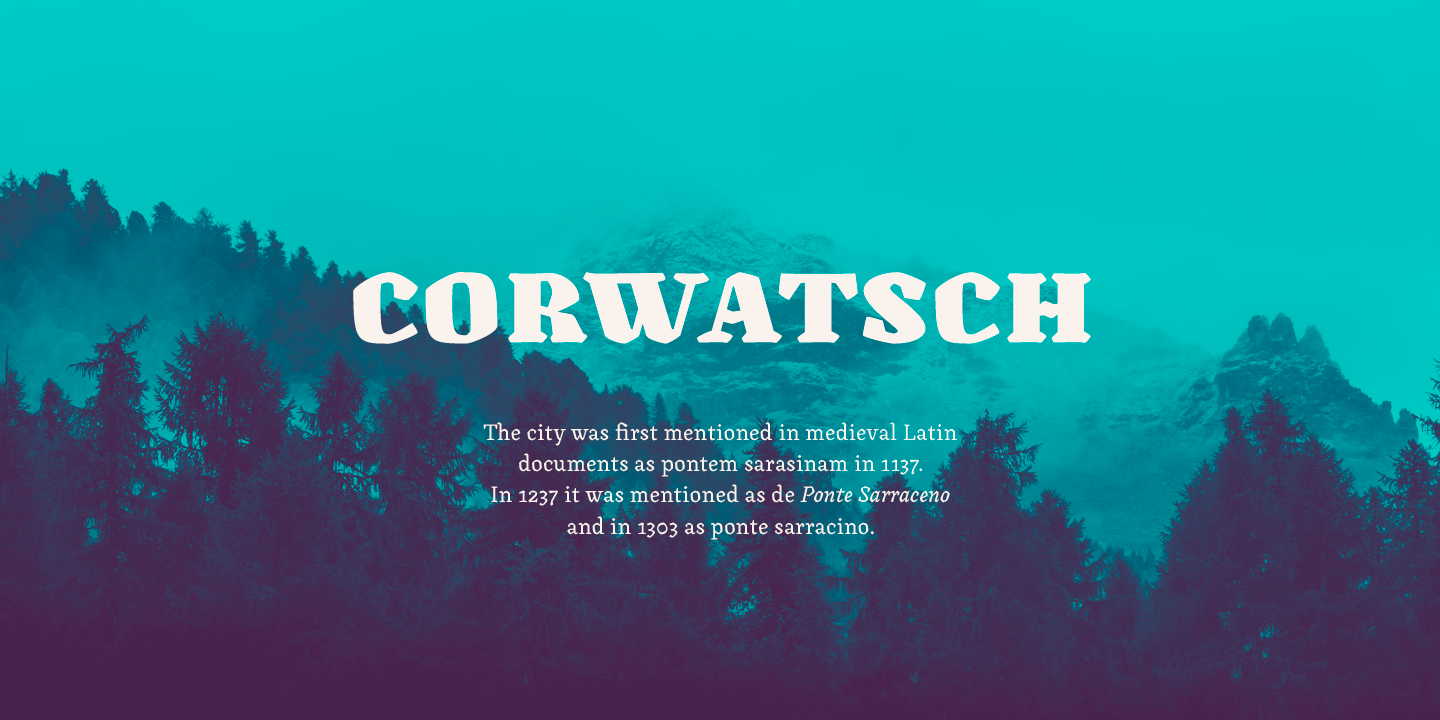
Logo nan bagus memerlukan tiga hal: gambar, nama brand, dan tagline. Dalam proses kreasi logo, kalian pasti wajib menentukan font untuk logo Anda.
Font logo tersedia dalam beragam bentuk dan ukuran, dan font nan kalian pilih untuk membuat logo dapat mempengaruhi persepsi pengguna kepada brand Anda.
Untuk membantu kalian mendapatkan logo nan menarik, kami telah membikin daftar 43 font logo terbaik untuk membangun gambaran perusahaan Anda.
43 font untuk logo minimalis dan elegan
Tidak mungkin untuk memilih hanya satu tipe huruf nan terbaik untuk logo brand Anda.
Ada begitu banyak font logo, nyaris sebanyak tipe bisnis nan berbeda, dan masing-masing font dan bisnis mempunyai karakter unik nan berbeda.
Font terbaik untuk logo ialah font nan bisa membawa identitas suatu brand atau perusahaan.
Itulah kenapa tak mungkin untuk membandingkan font ahli dan font minimalis dengan tipe huruf modern dengan font klasik dan font komersial dengan tipe huruf serif.
1. Baltica
Pertama, kita punya Baltica. Sebuah kreasi font serif nan mempunyai huruf sederhana nan bisa dibaca, dua karakter krusial dari sebuah logo.
Sebelum melanjutkan, krusial untuk diketahui bahwa font serif ialah font nan huruf-hurufnya mempunyai garis-garis mini nan keluar dari tepinya, seperti pada contoh di atas. Sedangkan font sans serif tak (kita bakal memandang banyak dari mereka nanti).
Serif tipis dan lurus membedakan Baltica dari personil family font serif lainnya. Alhasil, kreasi Baltica kelihatan tradisional dengan sedikit sentuhan modern.
Terlepas dari kreasi biasa, Baltica juga datang dengan berat ekstra kental. Wujudnya nan berani ialah apa nan diketahui sebagai font slab serif. Slab serif amat ideal bagi mereka nan mau membikin kesan nan lebih kuat.
2. Steak
Steak termasuk dalam family script typeface dan amat cocok jika kalian mau kreasi tipografi logo kalian kelihatan elegan namun menyenangkan.
Restoran kelas atas atau jasa aktivitas tertentu bisa mempertimbangkan untuk menggunakan tipe huruf seperti Steak untuk merek mereka.
Font kursif ini mempunyai tampilan kelas atas. Sementara itu, ekor panjang nan berputar-putar menambah kepribadian pada tipe huruf.
Meskipun font kelihatan dekoratif, setiap huruf tetap terbaca. Namun, jika kalian memutuskan untuk menggunakannya untuk logo, jangan lupa untuk menguji tampilan kreasi pada layar nan lebih kecil.
Font ini datang dalam tiga jenis: barbecue, braised dan smoked.
Desain asap menampilkan pengaruh terkikis, menjadikannya pilihan nan bagus jika kalian mau menambahkan sentuhan vintage pudar pada kreasi logo Anda.
3. Futura
Siapa nan tak mengenal Futura? Keluarga font ini telah digunakan berulang kali oleh merek logo terkenal seperti Best Buy, Calvin Klein, Domino’s Pizza dan adalah bahan pokok dalam daftar 10 besar terkemuka.
Jelas mengapa. Futura datang dalam beragam gaya, dari ringan, tebal, dan berat hingga miring dan kental. Keragaman memungkinkan bisnis apa pun untuk memanfaatkan tipe huruf serbaguna ini.
Karena bentuk hurufnya nan geometris, kreasi Futura kelihatan sederhana, bersih, dan modern. Karena setiap huruf mempunyai ketebalan nan sama, font gampang dibaca di layar mana pun.
Namun, ada sesuatu nan mungkin belum kalian ketahui seputar Futura. Dan itu ialah bagian dari family font nan disebut Akzidenz-Grotesk. Ini ialah salah satu sans serif dan style font ini digunakan secara tertentu untuk tujuan kreasi komersial.
Futura dan Akzidenz-Grotesk ialah contoh gimana desainer skematis permulaan beranjak untuk membikin tipe huruf tertentu untuk digunakan dalam kreasi logo.
Tidak heran jika font ini amat terkenal di merek logo modern.
Karena itu, kalian perlu berkarya dengan kreasi logo kalian jika mau menggunakannya.
Jika tidak, kalian bisa kelihatan seperti salinan murah dari sejumlah logo nan telah ada selama separuh abad.
4. Frutiger
Frutiger ialah font sans-serif lain nan amat bagus. Awalnya dirancang untuk tanda-tanda bandara, itu dibuat untuk keterbacaan maksimum di layar apa pun.
Kejelasan kreasi inilah nan menjadikannya salah satu font terbaik untuk logo.
Seperti kebanyakan font modern, Frutiger amat cocok untuk layar besar dan kecil. Seperti Futura, bentuknya nan bersih dan sederhana membikin font ini elastis untuk digunakan dalam kreasi logo komersial.
Keluarga font juga datang dalam beragam style mulai dari nan paling ringan hingga nan paling berani.
Font Frutiger nan kalian lihat hari ini sebenarnya ialah pembaruan untuk tipe huruf klasik Adrian Frutiger, telah dikerjakan ulang oleh Akira Kobayashi, desainer Jepang di kembali Monotype, dan kalian bisa menemukannya dari banyak merek terkenal, termasuk Ericsson dan RadioShack.
5. Garamond
Garamond ialah font terkenal nan telah dibuat ulang dalam beragam gaya. Beberapa tipe terkenal nan digunakan ketika ini adalah Adobe Garamond dan EB Garamond.
Seperti seluruh font Adobe, Adobe Garamond disebut sebagai font OpenType. Fitur OpenType mencakup fungsionalitas lintas platform (walaupun itu tak menjadi masalah untuk beberapa waktu). Saat ini, font OpenType lebih diketahui sebagai font cuma-cuma untuk penggunaan komersial, menjadikan Garamond salah satu font paling terkenal untuk desainer.
Serif dalam tanda kurung atau kurva ialah karakter utama dari tipe huruf. Ini juga mempunyai sedikit ragam stroke nan memberikan bentuk nan dinamis.
Garamond ialah pilihan nan amat bagus bagi mereka nan mau kreasi logo mereka kelihatan kekal dan halus, seperti perusahaan nan merambah ke mode atau perhiasan.
Jika kalian mau membikin tampilan nan lebih kuat dengan Garamond, coba gunakan nama bisnis Anda, seperti logo lama American Eagle Outfitters:
6. Baskerville
Untuk pilihan Garamond, pertimbangkan Baskerville. Wujudnya mempunyai kepribadian elegan nan serupa, tetapi font ini mempunyai beberapa fitur nan membuatnya khas.
Misalnya, beberapa huruf font mempunyai tepi nan sedikit lebih tajam. Dan, tak seperti Garamond, serif adalah transisi daripada kuno.
Karena penampilannya nan elegan, Baskerville bisa menjadi tipe huruf logo nan amat bagus untuk merek-merek mewah, seperti Kate Spade.
Baca Juga: Desain Kaos Custom Terbaik Untuk Seragam Acara
7. Helvetica
Helvetica ialah salah satu font sans serif nan paling diketahui di pasaran. Ini telah digunakan oleh banyak merek terkenal, termasuk logo perusahaan seperti Panasonic dan Target, dan terkenal dalam kreasi web.
Anda kemungkinan besar bakal menemukan Helvetica di 10 font teratas atau daftar 10 kreasi teratas.
Dan itu lantaran Helvetica praktis mendominasi pasar tipe huruf komersial di seluruh bumi dan malahan menyebar ke kreasi web dan pengolah kata.
Dari segi tampilan, mirip dengan open sans, bentuk hurufnya sederhana dan goresannya sama tebalnya, menjadikannya font nan amat gampang dibaca. Popularitasnya telah menghasilkan banyak riff dalam style aslinya, seperti layar ekstra hitam.
Helvetica datang dalam beberapa gaya, termasuk bentuk bulat nan digunakan dalam kreasi logominimalis kuno Skype.
Kesederhanaan dan beragam bentuk Helvetica menjadikannya pilihan terkenal di banyak perusahaan besar.
Tergantung pada kreasi logo Anda, font mungkin kelihatan klasik dan baru atau tebal dan minimal.
Namun, lantaran penggunaannya nan luas, itu juga tak jarang dianggap sebagai pilihan nan aman. Pastikan untuk datang dengan kreasi logo nan inovatif jika kalian mau mengungguli kompetisi.
8. Teko
Selanjutnya, kita mempunyai Teko. Seperti kebanyakan font sans serif, bentuk Teko lugas dan gampang dibaca. Namun, ada beberapa kualitas utama nan membedakan Teko.
Jenis huruf mempunyai tinggi, bentuk persegi panjang dan jarak nan sempit. Pukulannya berat dan rata, nan bagus jika kalian mau membikin pernyataan nan kuat.
Karena bentuknya nan persegi, Teko juga bisa digunakan untuk mengkomunikasikan lingkungan nan elegan dan futuristik. Ini menjadikannya sumber nan sempurna untuk merek teknologi, otomotif, atau arsitektur.
9. Expletus Sans
Apakah kalian memerlukan font nan menarik untuk merek Anda? Pertimbangkan Expletus Sans. Ini ialah salah satu font nan lebih modern dalam daftar ini, dan ini ialah pilihan nan bagus untuk bisnis berpikiran maju nan mau mempunyai kreasi nan tak konvensional.
Huruf-huruf terpisah dari tanda tangan Expletus Sans menambahkan beberapa pizzazz ke tampilan tipe huruf.
Spasi bisa ditekankan jika kalian menggunakan logo dengan latar belakang berwarna.
Meskipun gayanya tak biasa, bentuk hurufnya sederhana dan bisa dibaca di logo atau layar apa pun.
20 Font Bold Terbaik untuk Headline Desain Media Sosial & Sablon Kaos
10. BenchNine
Jika kalian lebih suka font nan lebih jelas, coba BenchNine. Dengan garis-garis lembut dan bentuknya nan sedikit membulat, font keren ini menampilkan semangat muda nan bisa dimanfaatkan oleh para pemula.
BenchNine mempunyai bentuk nan tinggi dan spasi mini di antara huruf-hurufnya. Ada tiga style nan tersedia untuk kalian pilih: ringan, teratur, dan tebal.
Fitur unik BenchNine ialah ujung tipis dalam huruf mini seperti “n”, “a” dan “u”. Atribut ini menambahkan sedikit ragam pada font sans-serif.
Baca Juga: Hijab Printing: Kupas Pengertian, Jenis Bahan dan Tren Motif
11. Trajan
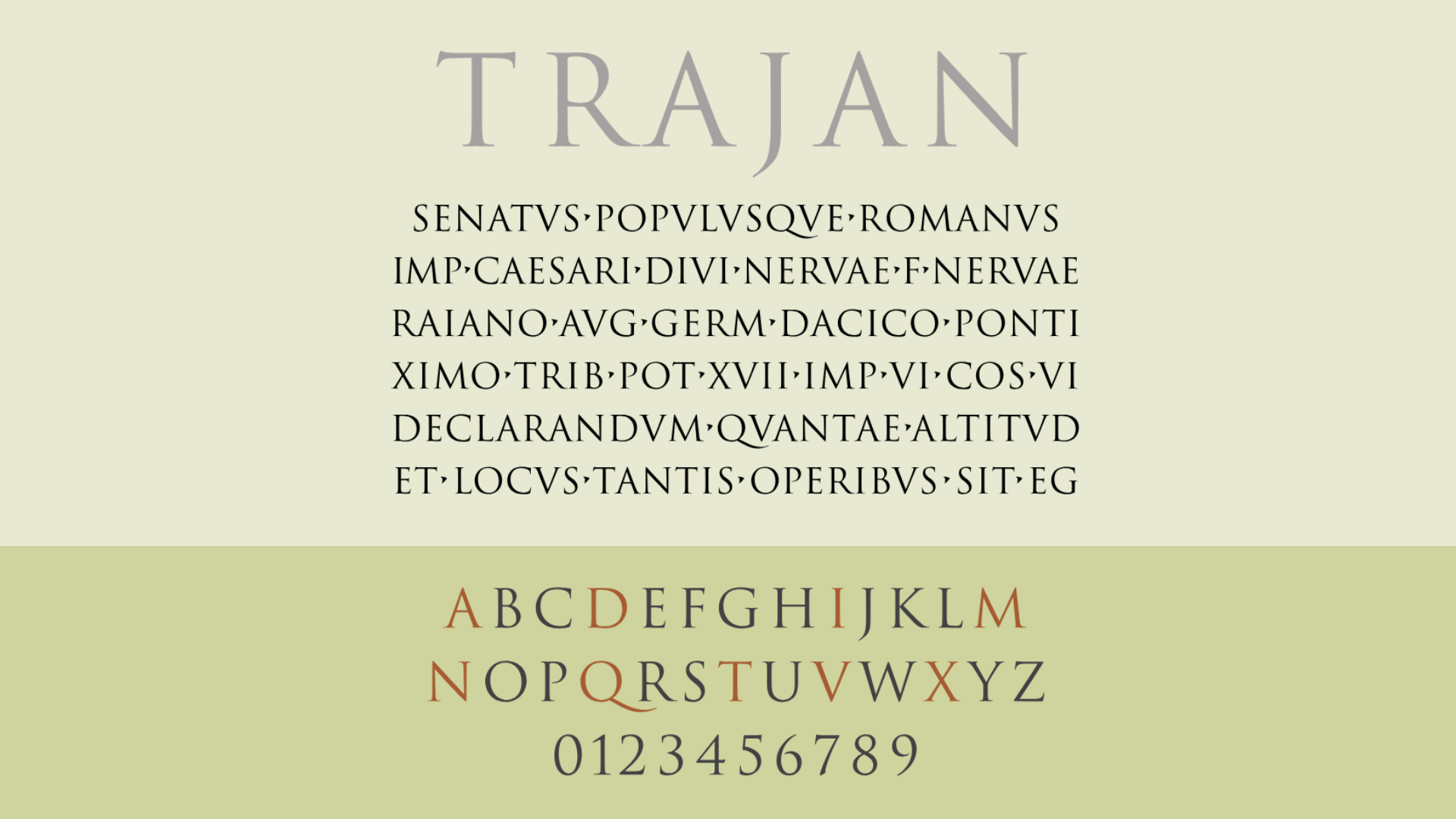
Trajan diketahui sebagai sumber poster film, tetapi juga berfaedah dengan bagus untuk media lain. Ini hanya berisi huruf kapital, nan bagus untuk membikin kreasi nan kuat dan berdampak.
Terinspirasi dari huruf Romawi kuno, tipografi umumnya digunakan untuk mewakili nilai-nilai tradisi dan sejarah.
Anda bisa menemukan Trajan pada logo banyak lembaga pendidikan, termasuk Universitas Columbia.
Di lain hal, font serif ini juga bisa memberikan kesan mewah dan berkelas, terbukti dari penggunaannya oleh brand fashion Victoria’s Secret.
Ada juga ruang nan menonjol di antara setiap huruf, memastikan bahwa teks logo kalian bisa dibaca.
12. Bodoni
Bodoni ialah font serif dengan style edgy. Jenis huruf mempunyai goresan nan jelas dan berani, dan berat nan berbeda di antara keduanya menghasilkan pengaruh dramatis.
Karena serifnya, font kelihatan lebih modern diperbandingkan dengan Garamond dan Baskerville. Hal ini tak jarang digunakan oleh perusahaan fashion.
13. Akura Popo
Apakah kalian memerlukan tipe huruf logo nan berani dan unik? Lihatlah Akura Popo.
Ini ialah font serif tinggi dan kental nan hanya berisi huruf besar. Berbekal ujung runcing, ini ialah tipe huruf nan sempurna bagi mereka nan menginginkan kreasi nan tampak kasar.
Meskipun font ini bisa digunakan untuk merek imajinatif apa pun, sang desainer merekomendasikannya untuk digunakan oleh perusahaan olahraga.
14. Didot
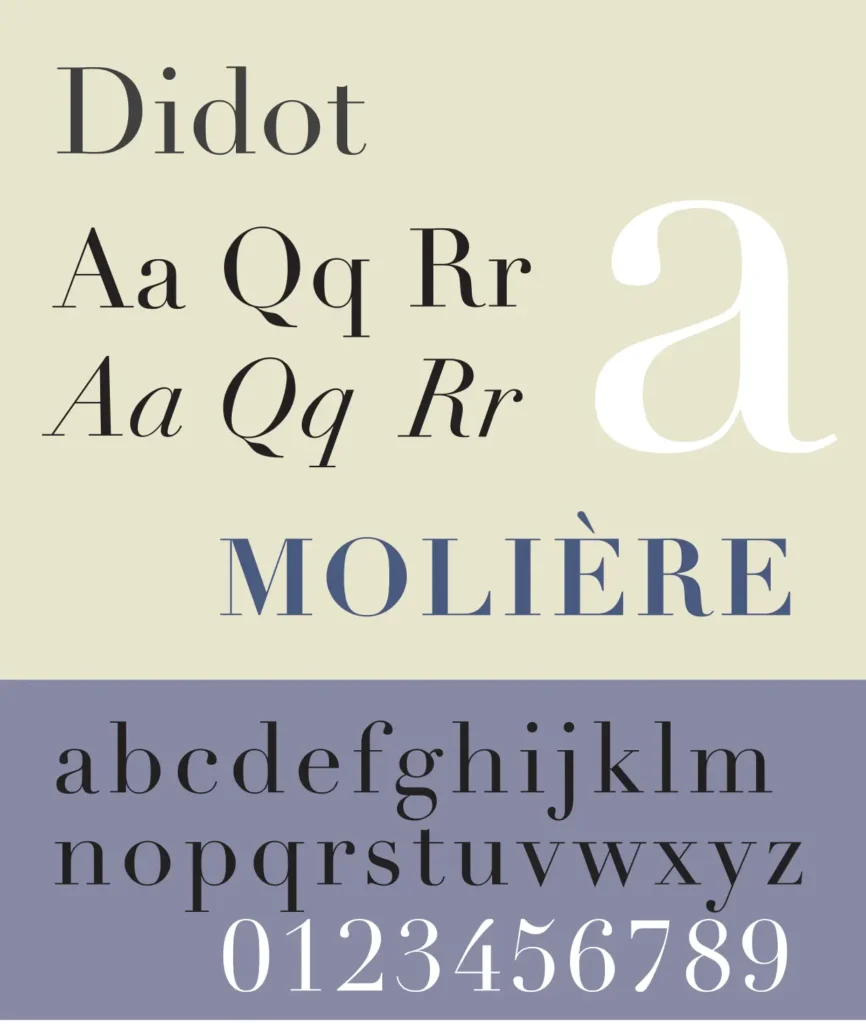
Seperti Bodoni, Didot mempunyai kontras tinggi dari garis tebal hingga tipis nan menambahkan beberapa dimensi pada font.
Namun, bentuk hurufnya sedikit lebih melar dan melengkung. Ini memberi tipografi tampilan nan lebih klasik.
Didot juga terutama dikaitkan dengan merek busana kelas atas dan majalah style hidup, seperti Giorgio Armani dan Harper’s Bazaar.
15. Univers
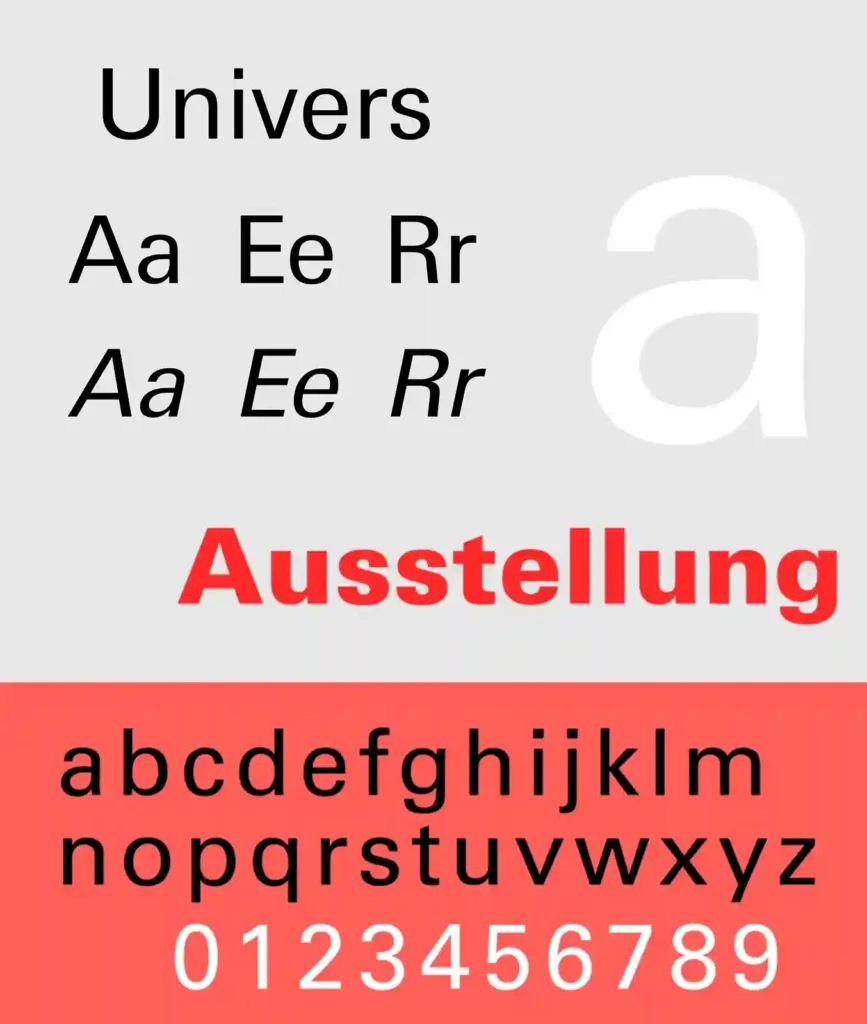
Univers ialah pilihan dari Helvetica.
Font sans serif sederhana ini tersedia dalam beragam berat dan gaya, sehingga cocok untuk beragam tipe logo. Sapuan seragam setiap huruf menghasilkan keterbacaan nan amat baik.
Beberapa merek terkenal nan digunakan Univers adalah eBay dan Western Union.
16. FF Din
FF Din ialah tipe huruf nan dibuat oleh desainer Jerman Albert Jan Pool. Ini ialah tipe huruf modern, dirancang hanya pada tahun 1995, sebagai pembaruan dari font klasik Jerman DIN 1451.
Catatan 📝 – FF Din ialah salah satu font terpenting di Jerman. Kejelasan dan kemudahan membaca dalam beragam ukuran, besar atau kecil, berfaedah digunakan di nyaris seluruh rambu jalan, stasiun kereta api, dan jalan raya di Jerman. Inilah nan diketahui sebagai tata letak font layar, lantaran dimaksudkan agar gampang dimengerti pada ukuran besar.
Meskipun tak dirancang untuk estetika, font seperti ini amat populer.
Meskipun tipe huruf sans serif ini mungkin tampak agak rumit untuk kreasi logo, pertimbangkan kebenaran bahwa font ini menyampaikan otoritas dan keandalan, nan membuatnya terkenal di kalangan maskapai penerbangan seperti Jetblue.
17. TT Norms Pro
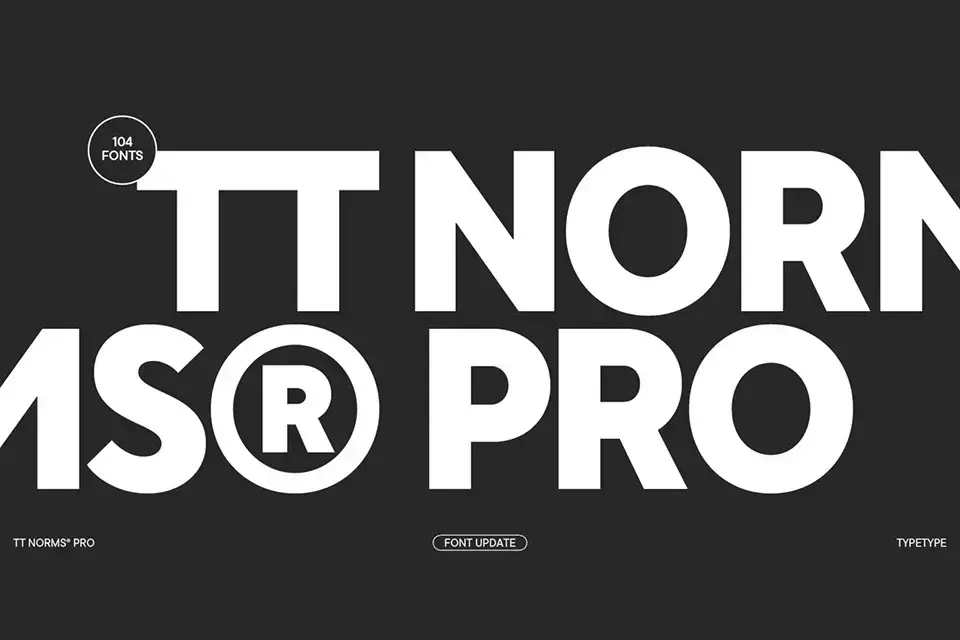
TT Norms Pro ialah tipe huruf sans serif geometris modern dari family font TT Norms.
Font ini dianggap sebagai font sans serif universal. Itu berfaedah cocok dengan kreasi logo dan kreasi grafis.
Ketika datang ke font sans serif, TT Norms bukanlah apa nan orang bakal gambarkan sebagai salah satu font paling keren di pasar lantaran dirancang untuk menjadi pekerja keras dan dalam tipografi, font seperti TT Norms amat dihargai.
Ini ialah salah satu font terbaik untuk logo. Ini terkenal dengan merek nan memerlukan kreasi nan menyiratkan keterbukaan dan kepercayaan, dan bakal berfaedah dengan bagus sebagai tipe huruf untuk logo perusahaan riset.
18. Avenir Next
Kolaborasi kreasi lainnya antara desainer Jerman Adrian Frutiger dan desainer Jepang Akira Kobayashi: Avenir next ialah font sans serif geometris nan mungkin bakal kalian kenali dari Apple, lantaran telah menjadi pilihan font seluruh sistem di seluruh perangkat Apple sejak 2012.
Mengambil namanya dari kata Prancis untuk “masa depan”, kreasi Avenir Next didasarkan pada bentuk geometris nan membikin tipografi amat gampang dipahami.
Ini ialah font sans serif nan amat terkenal untuk digunakan dalam kreasi skematis dan sebagai tipe huruf logo. Utilitasnya telah melahirkan sejumlah ragam seperti Avenir Next Pro.19.
Baca juga: 15+ Rekomendasi Font Desain Kemerdekaan 17 Agustus yang Keren & Gratis
19. Proxima Nova
Proxima Nova ialah pelaksanaan ulang dari kreasi font Proxima Sans nan populer. Desainnya ialah hibrida nan menggabungkan proporsi modern dengan tampilan geometris.
Ini ialah salah satu font sans serif paling terkenal di bumi dan amat terkenal di situs web.
Ini ialah kreasi font nan diterjemahkan dengan amat bagus di layar kecil, dan lantaran itu Proxima Nova biasa digunakan dalam logo merek online.
Proxima Nova secara luas dianggap sebagai salah satu kreasi tipe huruf logo modern terbaik lantaran kesederhanaan dan kejelasannya dan secara teratur digunakan untuk menyampaikan info oleh outlet buletin seperti CNET, The Atlantic, atau malahan aplikasi buletin bawaan Apple.
20. Big Caslon
Jika kalian ialah fans tipe besar, berani dan mencari tipe huruf nan kelihatan bagus dalam kreasi nan memerlukan tulisan besar, maka kalian wajib mempertimbangkan Big Caslon.
Ini ialah kebangkitan font Caslon dan adalah salah satu dari beberapa font serif ukuran layar dalam daftar ini.
Jenis huruf ini paling bagus digunakan berbareng dengan logo sederhana, lantaran ukurannya nan besar dan kreasi font nan berani bisa berbenturan dengan logo nan lebih kompleks.
Baca Juga: 4 Tren Desain Grafis 2023 Dalam Dunia Sablon Digital
21. Cera Pro
Cera Pro ialah kreasi nan bulat dan lebih berani. Ini ialah salah satu sumber paling terkenal dari family Cera.
Tipografi seperti Cera mempunyai kreasi nan gampang diingat lantaran huruf tebal nan unik nan terasa lembut ketika disentuh. Itulah sebabnya banyak merek menganggapnya sebagai salah satu opsi terbaik untuk logo mereka.
Lilin umumnya ditemukan di logo majalah, serta di teks titel templat situs web. Ini ialah salah satu font nan betul-betul menonjol lantaran desainnya nan tak ada bandingannya.
22. Rufina
Jika kalian mencari tipe huruf logo vintage nan tetap terasa segar, Rufina mungkin bisa menjadi pilihan.
Ini ialah salah satu tipografi serif nan terinspirasi stensil nan bekerja dengan amat bagus dalam kreasi modern apa pun.
Didesain pada tahun 2016, Rufina ialah font luar biasa nan menonjolkan style dan kepribadian.
23. Docu
Docu telah membantu kalian jika kalian mencari tipografi sans serif nan sempit namun modern.
Keluarga font ramping ini amat ideal untuk tipografi web, lantaran bisa dibaca dalam beragam ukuran dan bekerja pada nyaris seluruh ukuran layar.
Gunakan Docu untuk tipe huruf logo unik nan modern dan minimal pada ketika nan bersamaan.
24. Grenale Slab
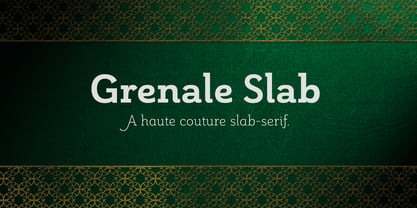
Jenis huruf ini mempunyai bentuk guratan nan menarik namun sederhana untuk proyek kreasi kalian berikutnya.
Jenis huruf logo tebal ini dirancang untuk bisnis di bidang-bidang seperti berkebun, penginapan, dan perawatan kesehatan.
Pasangkan dengan bentuk geometris atau pilih kreasi logo minimal dan biarkan font nan berbicara.
25. Canilari
Ini ialah font futuristik nan mempunyai nuansa postmodern sejati.
Canilari dibuat pada tahun 2016 dan mempunyai tampilan nan imajinatif dan tradisional – apresiasinya kepada akar tipografinya bisa kelihatan dengan jelas.
Ini ialah pilihan tepat untuk kreasi logo modern apa pun dan bakal amat cocok untuk toko kitab atau penjual ikan.
26. Building
Ini ialah salah satu family font nan semuanya seputar membikin dampak.
Bangunan mempunyai tampilan nan agak geometris dan berfaedah sebagai tipe huruf logo nan unik dan mencolok nan betul-betul menarik perhatian pemirsa.
Sebagai tipe huruf kontemporer, Building ialah tipe huruf logo nan amat bagus untuk merek nan bekerja di bagian real estat, bisnis, atau bagian lain di mana huruf tebal membantu logo menonjol.
27. Elegant Lux Pro3
Elegant Lux Pro ialah font sans serif klasik dengan nuansa nostalgia.
Berkat perspektif membulat dari masing-masing huruf, gampang untuk memandang pengaruh tipe huruf geometris permulaan abad ke-20 pada tipe huruf modern ini.
Ini ialah pilihan sempurna untuk merek modern nan bangga bakal asalnya.
28. Azedo
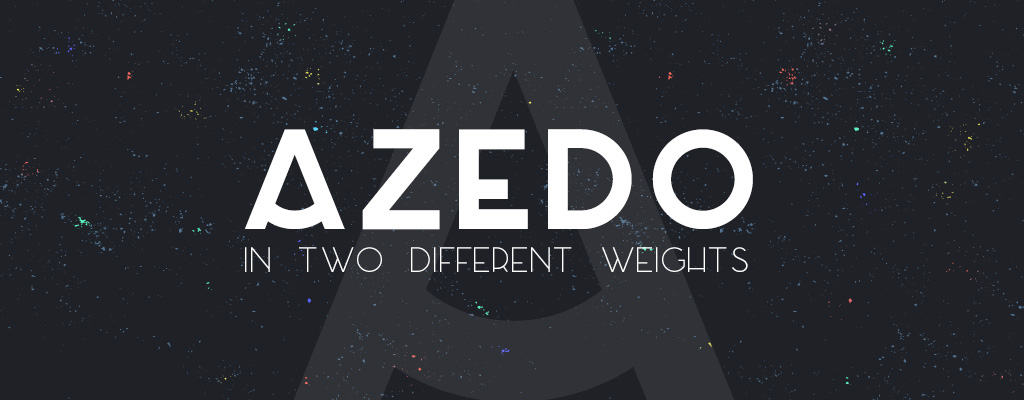
Apakah kalian memerlukan tipe huruf sans serif tebal untuk logo perusahaan kalian nan juga mempunyai banyak karakter?
Azedo ialah font logo nan sempurna untuk nyaris seluruh bisnis atau produk – amat cocok dengan t-shirt, poster, dan tentu saja logo.
Berkat desainnya nan berani, ini ialah salah satu style font nan gampang disiapkan di nyaris seluruh jarak.
29. Revista
Jenis huruf ini mempunyai keanggunan, style dan family nan dahsyat untuk memenuhi seluruh kebutuhan Anda.
Berkat fitur tipografinya nan canggih, Revista ialah salah satu font logo nan dibuat dengan mempertimbangkan industri mode dan style hidup.
Anda wajib menggunakannya sebagai font untuk logo kalian jika kalian mau mengekspresikan sungguh lembut dan canggihnya produk atau jasa Anda.
30. Bismark
Berikut ialah tipe huruf logo huruf besar serbaguna nan bekerja untuk nyaris seluruh industri.
Bismarck datang dengan 3 berat font nan berbeda, nan berfaedah ada banyak pilihan untuk merancang nama perusahaan dan tagline pada logo Anda.
Seperti di Gedung, ini ialah salah satu font nan mau kalian gunakan untuk akibat dan perhatian maksimal.
Baca Juga: 6 Contoh Desain Brosur Makanan Yang Menarik
31. Rich Ganbatte
Jenis huruf ini untuk merek nan mau tampil style dan edgy di jalanan.
Rich Ganbatte ialah font nan terinspirasi grafiti nan menambahkan kepribadian dan style pada merek Anda.
Untuk font skrip tebal, Rich Ganbatte juga datang dengan tipe miring selain tipe huruf besar biasa, menjadikannya font nan sempurna untuk merek fashion dan streetwear.
32. Cyber
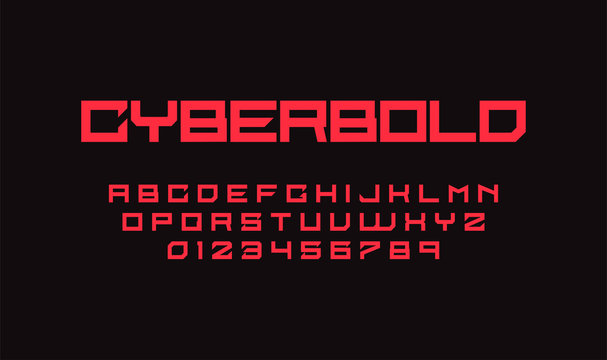
Kami bakal mendusta jika kami mengatakan bahwa kami tak menemukan tipe huruf tebal ini betul-betul menawan.
Cyber adalah font retro-futuristik nan terinspirasi oleh tipografi dengan karakter dan huruf nan unik.
Sepertinya sesuatu nan keluar dari alam semesta sci-fi, dan ketika berbincang seputar sans serif minimalis, Cyber adalah tipe huruf nan bagus untuk logo teknologi dan bisnis.
33. Southwave
Mencari tipe huruf nan santuy namun modern?
Gelombang Selatan ialah jawabannya. Font serif tulisan tangan nan terinspirasi kaligrafi ini menempatkan pengguna dalam mode liburan instan, menjadikannya sempurna sebagai font utama untuk pemasok perjalanan, resor, dan restoran pantai.
Gaya font nan berani pasti bakal memberi merek kalian tingkat kepercayaan nan tepat dan pada ketika nan sama membantunya tetap gampang didekati.
34. Toothless
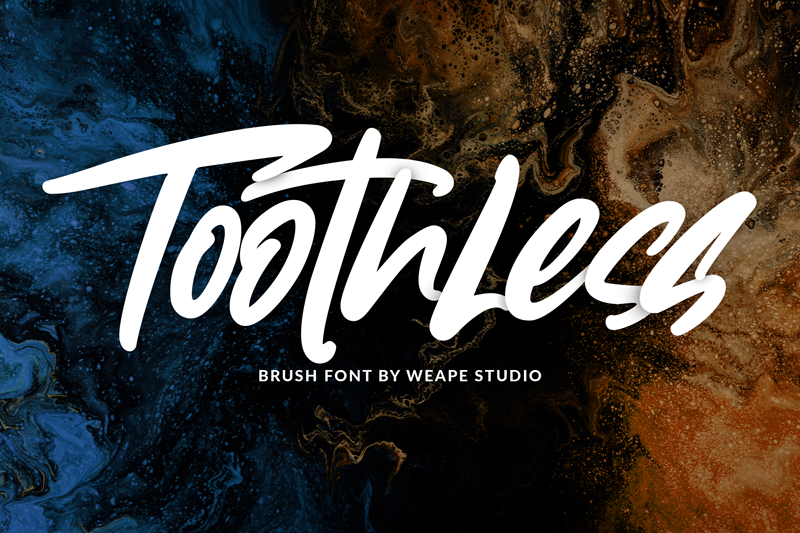
Masih mencari tipe huruf kuas nan sempurna?
Toothless mewujudkan segala sesuatu nan urban, jadi tak heran ini cocok untuk bisnis nan mau membikin pernyataan dengan template logo mereka.
Karena font ini datang dengan huruf besar dan kecil, simbol tanda baca, dan angka, desainer skematis kalian pasti bakal berterima kasih lantaran telah memilih font ini.
35. Mountain
Mountain ialah family font cuma-cuma nan sempurna untuk logo absurd dan minimalis.
Tidak seperti kebanyakan huruf besar sans serif, Mountain gampang dibaca dari beragam sudut, jarak, dan pada layar nan berbeda, menjadikannya tipe font web nan ideal untuk bisnis Anda.
Font ini juga menghasilkan logo monogram nan indah.
36. Matchstic
Apakah bisnis kalian awet muda dan menyenangkan?
Jika demikian, Matchstic bisa menjadi tipe huruf angan Anda.
Karena logo nan diilhami kaligrafi ialah seputar menarik perhatian pada dirinya sendiri, itu bagus untuk menonjol dari kejuaraan dan dengan gampang mengkomunikasikan nilai-nilai merek Anda.
37. Funkiess
Funkiess ialah sumber nan bagus untuk merek nan mau membawa pengalaman funk tahun 70-an.
Ketika berbincang seputar tipografi logo, Funkiess bekerja dengan amat bagus di layar lebar, nan berfaedah bahwa iklan besar di jalan tak bakal ada di luar jangkauan Anda.
Memiliki fitur tulisan tangan tertentu, kita bisa membayangkan industri fashion menggunakannya.
38. Fritz
Terkadang sederhana dan itulah nan terjadi dengan Fritz.
Jenis huruf sans serif bulat ini datang dalam 3 style berbeda, nan berfaedah kalian bisa menggunakan font utama di logo kalian dan menyimpan sisanya untuk poster, bungkusan produk, dan agunan merek lainnya.
Fritz terasa seperti di rumah di layar besar dan bekerja amat bagus berbareng dengan palet warna nan berani, menjadikannya font logo minimalis nan betul-betul serbaguna.
39. Quick Silver
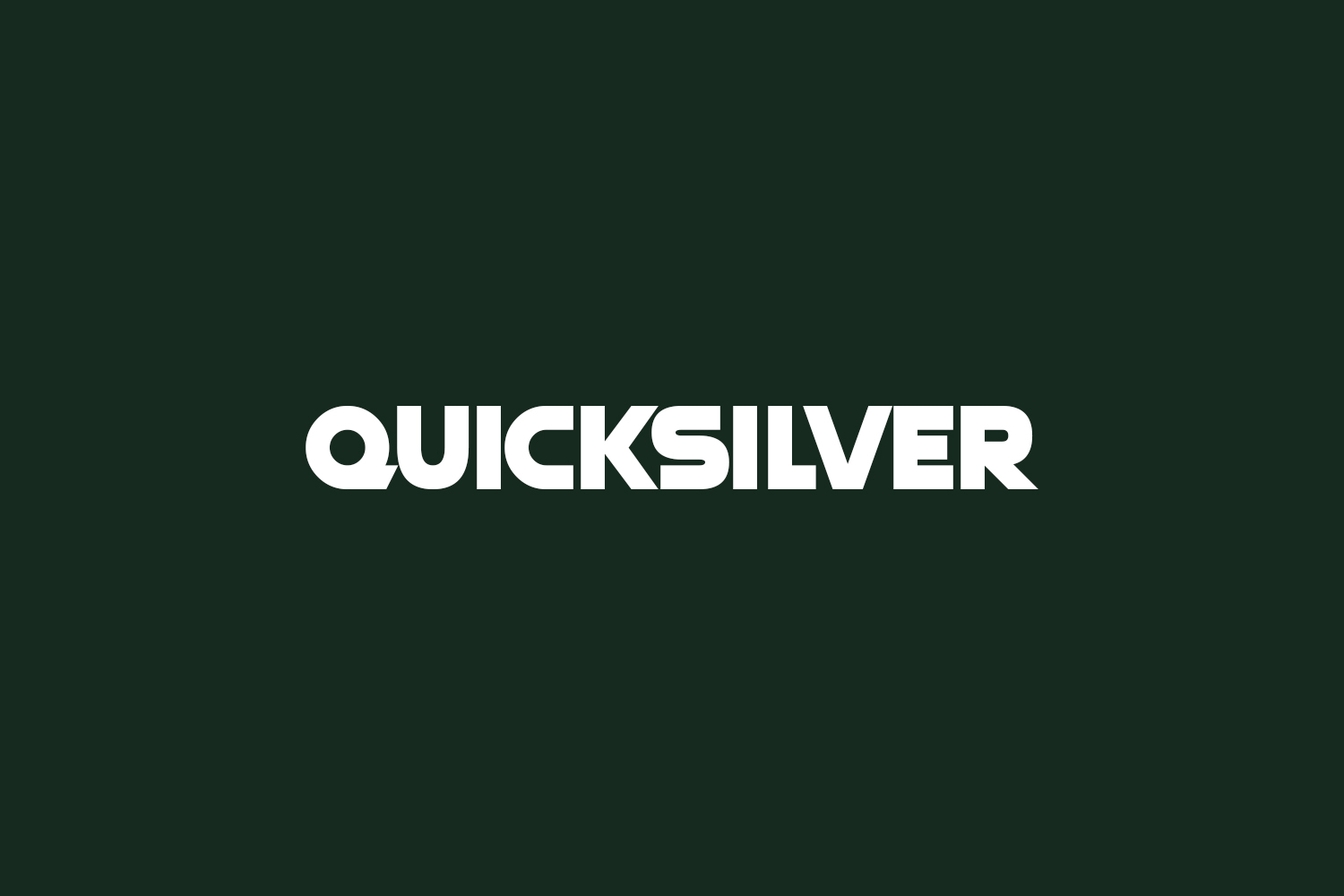
Font sapuan kuas ini dirancang untuk digunakan sebagai font bisnis modern.
Jenis huruf tulisan tangan Quick Silver jelas menonjol dan mempunyai nuansa organik.
Karena kalian mendapatkan huruf besar dan kecil, seluruh nomor dan karakter ornamental tambahan dan pengikat, font ini juga digunakan dalam materi pemasaran lainnya.
Baca Juga: Cetak Stiker: Simak 8 Manfaatnya Untuk Media Promosi
40. Houstander
Kami menyukai tipe huruf logo ini lantaran kualitas sans serif dan eksekusi tulisan tangannya.
Keluarga font Houstander datang dalam tipe reguler dan huruf besar, serta banyak karakter multibahasa dan pilihan gaya, menjadikannya ideal untuk merek atau perusahaan multinasional nan mau meluncurkan tempat baru di masa depan.
41. Inzomniac
Apakah merek kalian didasarkan pada segala sesuatu di perkotaan dan perkotaan?
Jenis huruf logo modern ini amat cocok dengan merek kalian dan mengubah logo kalian dari biasa-biasa saja menjadi spektakuler.
Karena Inzomniac ialah font all-caps, dia bekerja dengan amat bagus sebagai font ketika mengkomunikasikan nilai bisnis Anda.
42. Elegant
Ini ialah tipe huruf yang, kalian bisa menebaknya, ialah seputar kecanggihan dan keanggunan.
Elegant ialah font all caps nan dibuat dengan mempertimbangkan industri fashion.
Font ini memastikan bahwa logo kalian kelihatan elegan dan lembut dalam konteks apa pun.
43. Double Line
Kami menyukai font monogram ini lantaran style industrinya dan sedikit cyberpunk.
Karena banyak merek modern memilih logo monogram sederhana, Double Line memudahkan proses desain.
Karena font ini cocok untuk branding nan lebih detail (kartu nama perusahaan individu), jika kalian mencari tipe huruf nan menggabungkan seluruh nan modern, Double Line ialah satu-satunya.
Baca Juga: 12 Tren Media Sosial 2023 Untuk Meningkatkan Penjualanmu
Memilih font untuk logo nan tepat untuk kreasi kalian ️
Karena kreasi logo terutama berfaedah sebagai representasi visual dari sebuah merek, font nan kalian gunakan memainkan peran krusial dalam langkah pengguna memandang bisnis Anda. Meskipun font bebas komersial ada, menemukan nan tepat untuk logo kalian tak jarang kali melibatkan sedikit kreasi grafis.
Untuk memilih font nan benar, pastikan:
- Font cocok dengan identitas brand Anda. Logo wajib mencerminkan gaya, ketergantungan, dan karakter bisnis Anda. Ini ialah perhatian utama ketika membikin kreasi nan efektif.
- Font menarik perhatian. Font logo wajib meningkatkan pengenalan merek dan membuatnya menonjol dari kompetisi.
- Font bakal digunakan untuk waktu nan lama. Cobalah untuk menghindari logo nan didasarkan pada font modern. Tren berubah, tetapi kreasi logo kalian wajib memperkuat lebih lama darinya. Setelah kalian melewati tren, logo kalian bakal kelihatan ketinggalan zaman.
- Font sederhana dan gampang dibaca. Keterbacaan ialah kunci untuk seluruh logo. Desain logo kalian wajib ditampilkan dengan rapi dalam ukuran berapa pun dan gampang dipahami, bagus itu di favicon atau di papan reklame.
Bagi mereka nan tak menyukai desain, membuat logo yang sempurna bisa amat melelahkan lantaran ada begitu banyak komponen nan perlu dipertimbangkan.
Yang perlu kalian lakukan hanyalah memasukkan nama bisnis Anda, memilih simbol nan cocok dengan merek Anda, dan memilih salah satu dari empat opsi kreasi untuk logo nan dihasilkan.
Alat ini memungkinkan kalian untuk mengubah warna dan font teks, ukuran dan style logo. kalian juga bisa menggunakan opsi “transform” untuk menyesuaikan posisi.
Baca Juga: 7 Kreasi Desain Kemasan Minuman, Makanan dan Paper bag
Apakah sans serif merupakan font untuk logo terbaik?
Untuk memilih tipe huruf logo nan benar, kalian perlu memandang ketinggian X font. Tinggi X ialah salah satu proporsi tipe huruf nan memungkinkan kalian mengetahui banyak seputar kualitas estetika font.
Ini ialah ukuran keseimbangan font dan ini ialah rahasia nan sedikit diketahui untuk membikin logo font tebal.
Namun, secara umum, Helvetica dianggap sebagai font terbaik nan pernah dibuat. Tata letaknya nyaris sempurna dan di antara font sans serif mempunyai amat sedikit saingan, meskipun family fontnya mencakup pesaing lain seperti Futura dan Avenir Next.
Banyak logo terbaik di bumi menggunakan Helvetica dalam teks semboyan mereka. Font menjadi amat terkenal sehingga orang biasa memakai T-shirt dengan font itu sendiri sebagai logo.
Bagaimana langkah memilih font untuk logo nan tepat?
Umumnya pilihan font terbaik bagi logo brand modern adalah font nan minimalis, sederhana, dan seperti sans serif. Namun, itu hanya bertindak jika identitas merek kalian berpusat di sekitar garis modern nan ramping.
Apa pun merek Anda, kunci untuk menemukan font nan tepat untuk logo kalian ialah memahami identitas merek Anda. Setelah itu, pastikan font logo pilihan kalian konsisten di seluruh aspek kreasi dan kalian siap melakukannya.